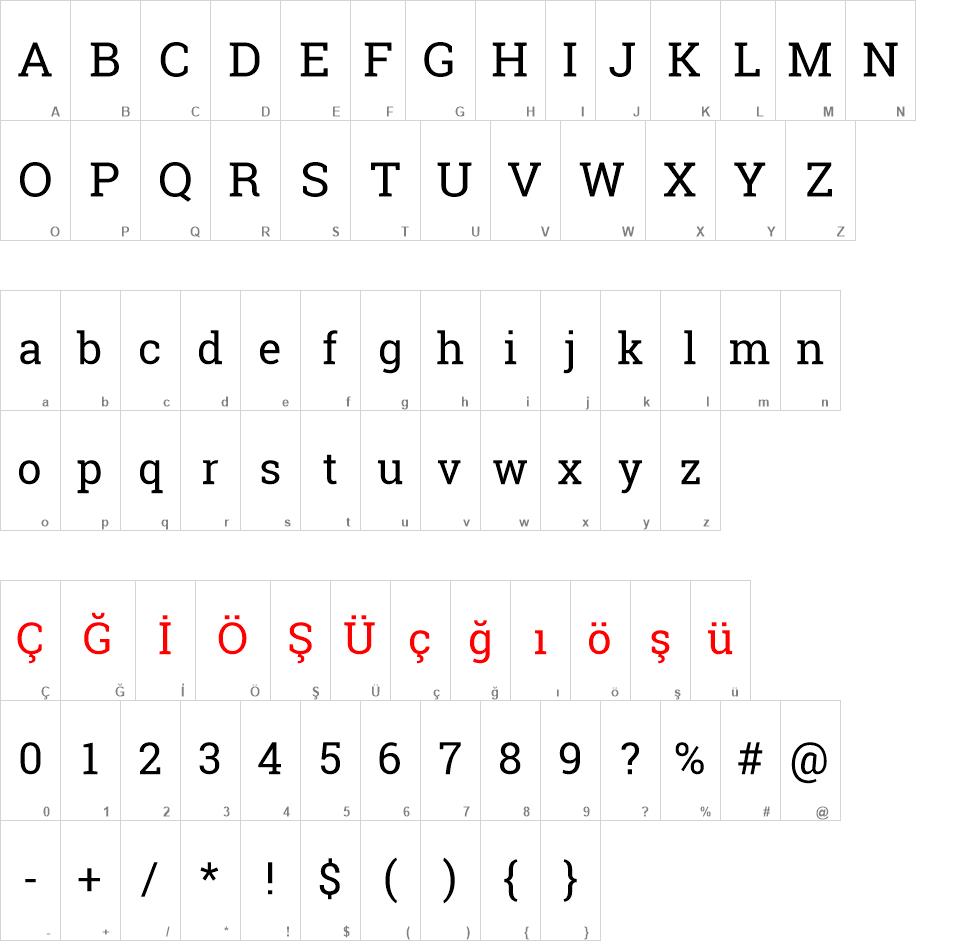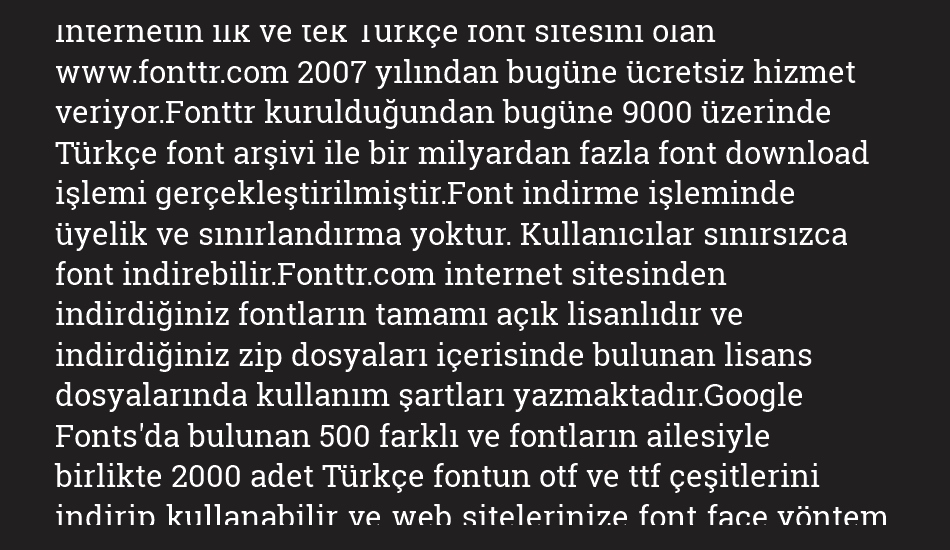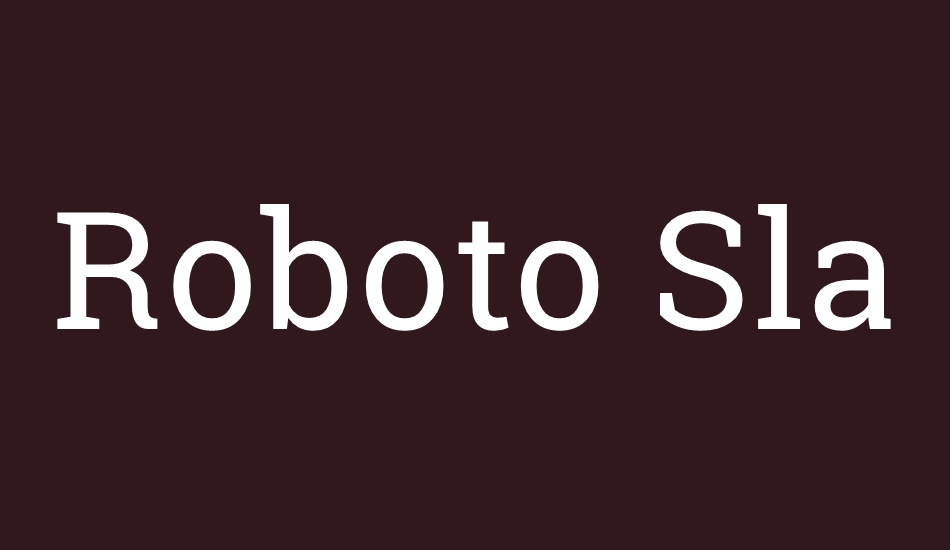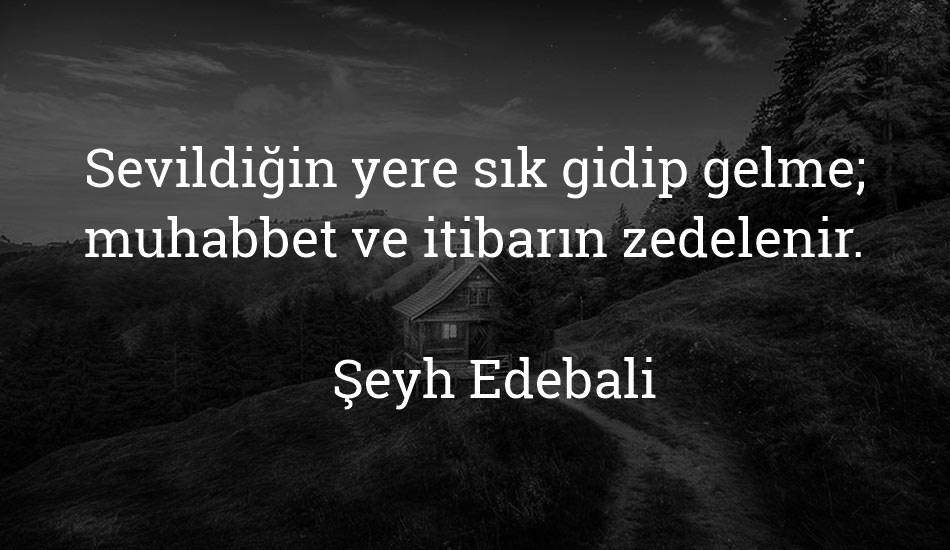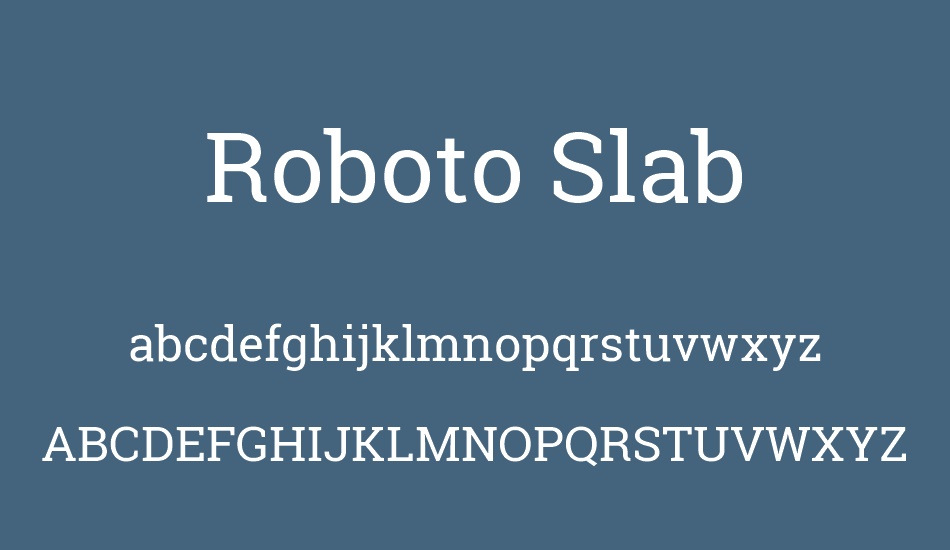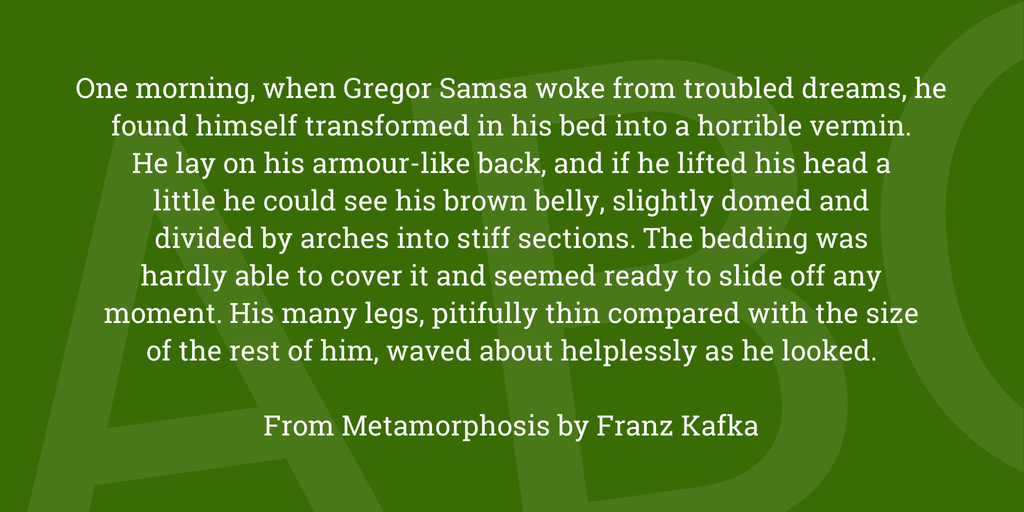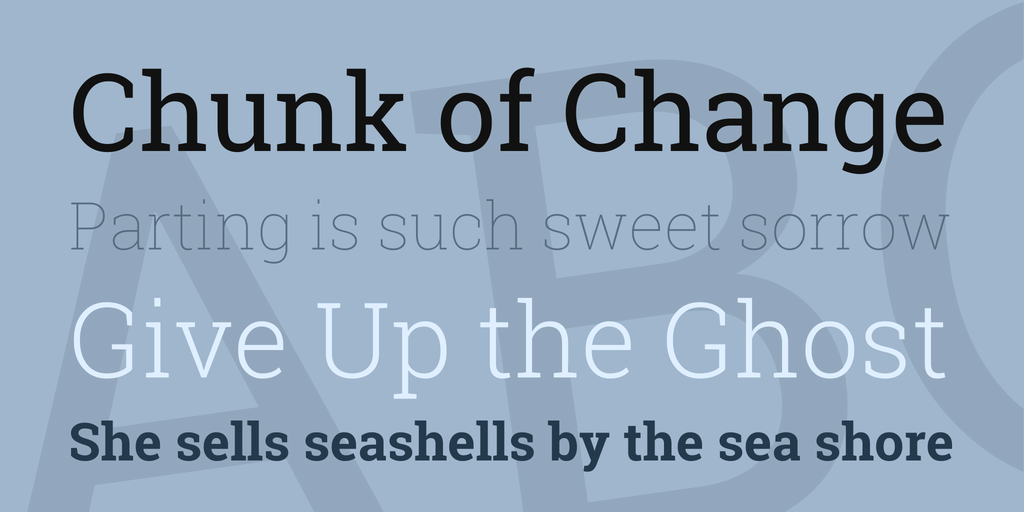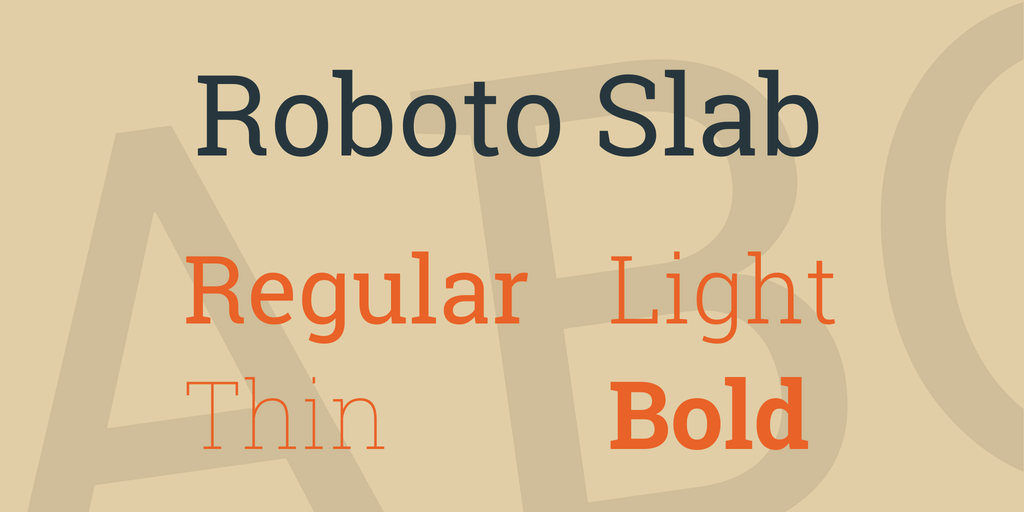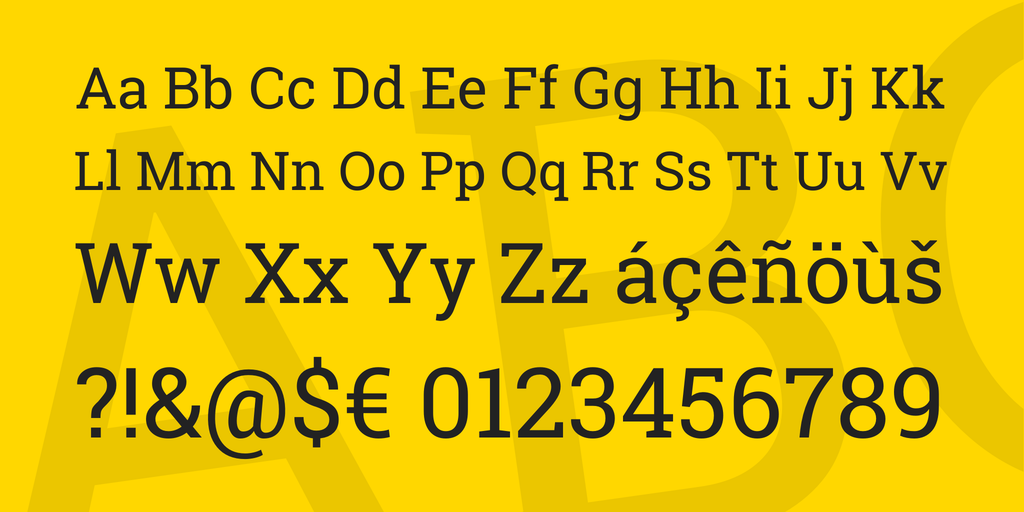
Roboto Slab font
Roboto'nun ikili bir doğası var. Mekanik bir iskelet vardır ve formlar büyük ölçüde geometriktir. Aynı zamanda, yazı tipi kolay ve açık eğrilere sahiptir. Bazı grafikler, mektup biçimlerini sert bir ritmi zorla kullanmak için bozarken de, Roboto uzlaşma sağlamaz ve harflerin doğal genişliklerine yerleşmesine izin verir. Bu, hümanist ve serif türlerinde daha sık rastlanan daha doğal bir okuma ritmini sağlar.
Roboto Slab font 4 adet font stilinden oluşur.